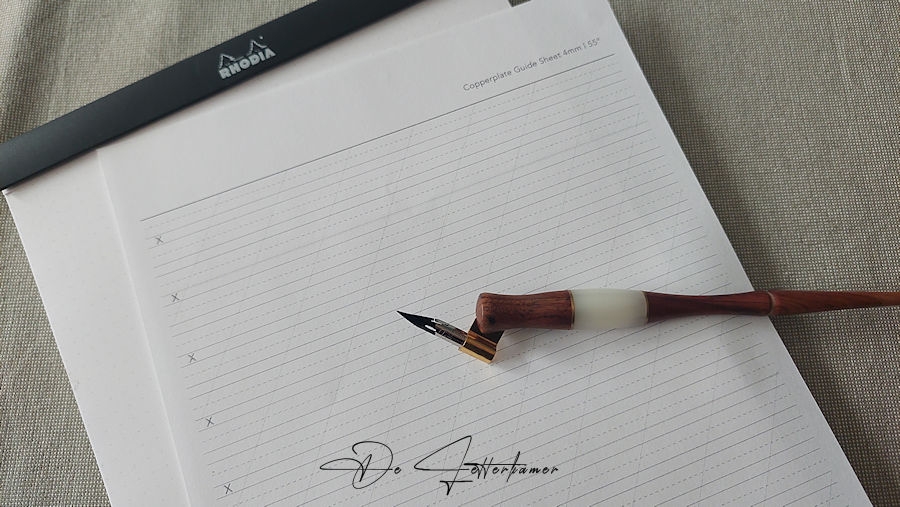
Er was mij iets opgevallen bij de guidelines, dit kan per boek verschillen, dus ik ben even mijn licht gaan opsteken op Google en ja, bij Copperplate bestaan er verschillende soorten guidelines (hulplijnen), en ze kunnen afhankelijk van de methode of het oefenboek iets verschillen. De basis blijft echter vast.
De belangrijkste lijnen
Bij Copperplate werk je meestal met:
- Baseline – de lijn waarop de letters staan.
- Waist line / x-height – de hoogte van de kleine letters.
- Ascender line – waar de lussen van bijvoorbeeld b, d, h, k, l komen.
- Descender line – waar de lussen van f, g, j, p, q, y naartoe gaan.
- Slant lines – schuine hulplijnen die de schrijfhoek aangeven (55°)
De schuine lijnen staan op 55°. Dit is heel gebruikelijk voor Copperplate.
Verschillende verhoudingen van de letterhoogte:
Bijvoorbeeld:
- x-height = 1 deel
- ascender = 2 delen
- descender = 2 delen
Maar je kunt ook 3:2:2, 3:3:3 enz. tegenkomen, afhankelijk van de stijl en het oefenboek.
Bij Copperplate moet je onderscheid maken tussen: de helling van het papier en de helling van de letters. Het papier wordt dikwijls zo gedraaid dat de schrijfbeweging natuurlijk langs de schuine hulplijnen loopt. Je hoeft dus niet per se recht tegenover het blad te zitten.
1 : 1 : 1 dit geeft relatief kleine letters met korte lussen. Hierbij zijn de afstanden ongeveer gelijk
────── Ascender
↑ 1
────── Waist / x-height
↑ 1
────── Baseline
↑ 1
────── Descender
1 : 2 : 2 Dit is een heel bruikbare klassieke verhouding, dit geeft de typische lange, elegante Copperplate-lussen.
────── Ascender line
│
│ 2
────── Waist line
│ 1
────── Baseline
│
│ 2
────── Descender line
x-height = 1 deel
ascender = 2 delen
descender = 2 delen
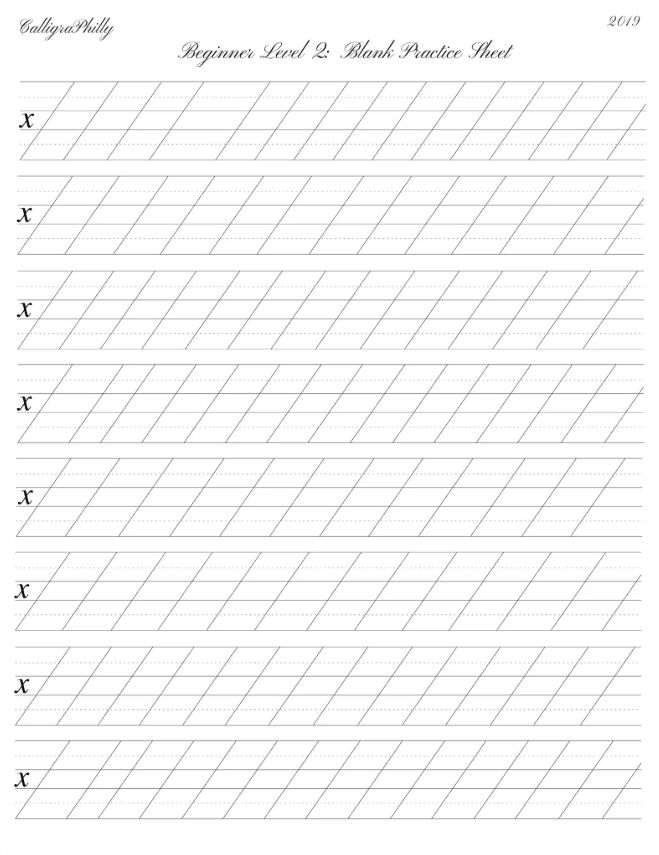
Voor klassieke Copperplate wordt 1:2:2 heel vaak gebruikt als praktische verhouding voor oefenbladen.
Bijvoorbeeld met een x-height van 5 mm:
Ik ga nu wat enkele kopieën maken uit het boek van Christen Allocco Turney. En op deze manier eens proberen letters te schrijven.
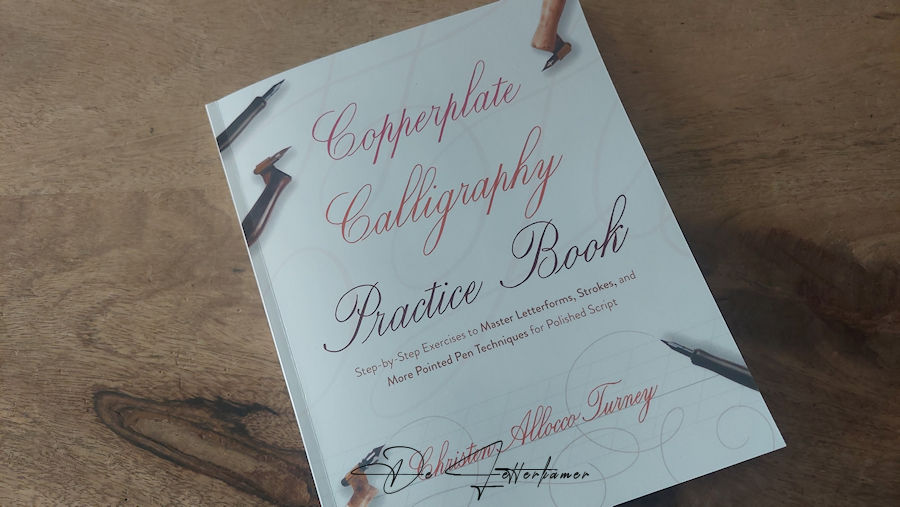
Zeer interessant oefenboek.